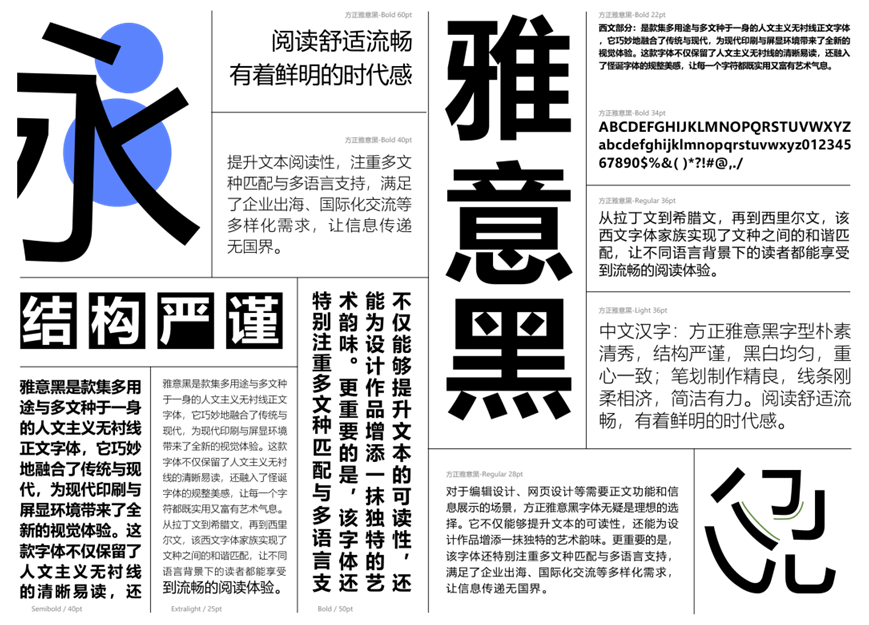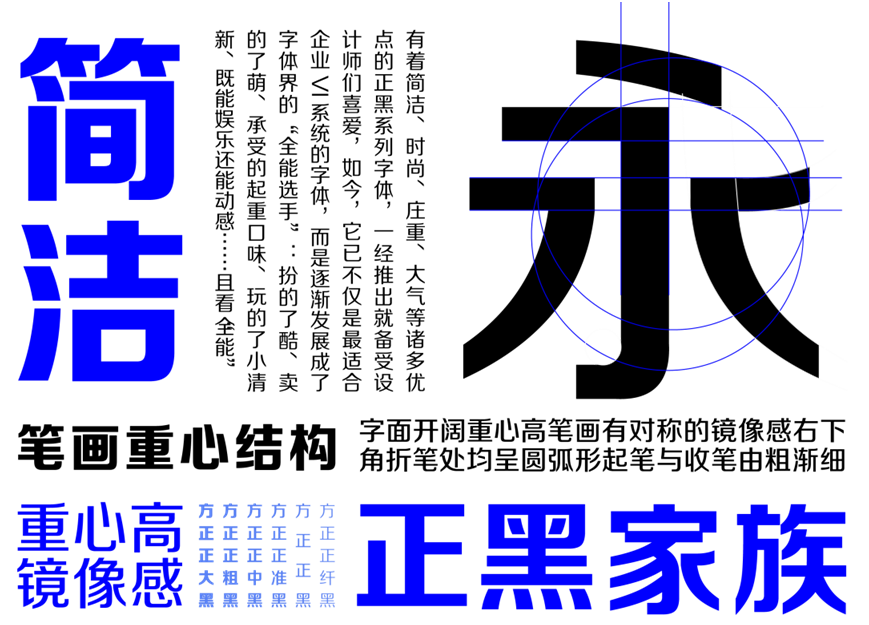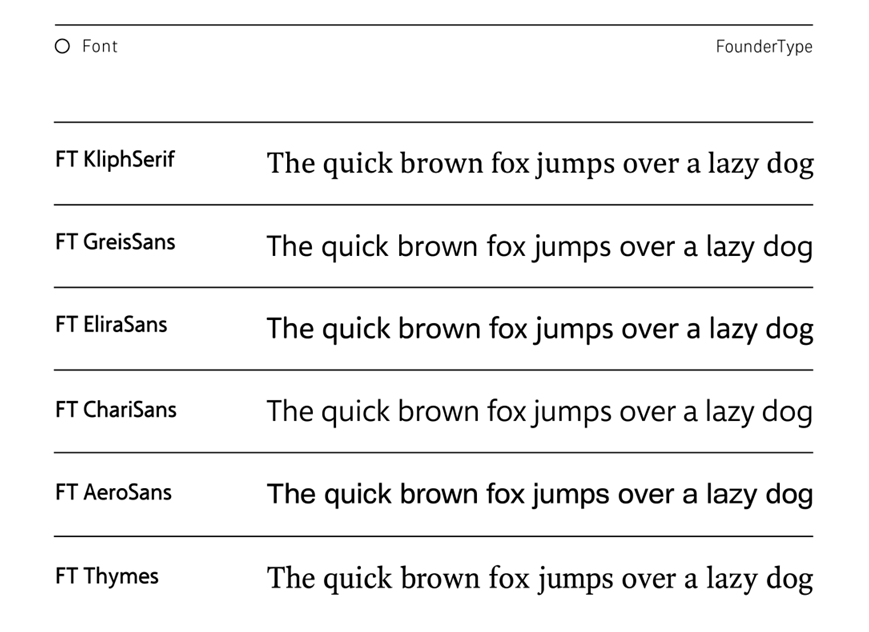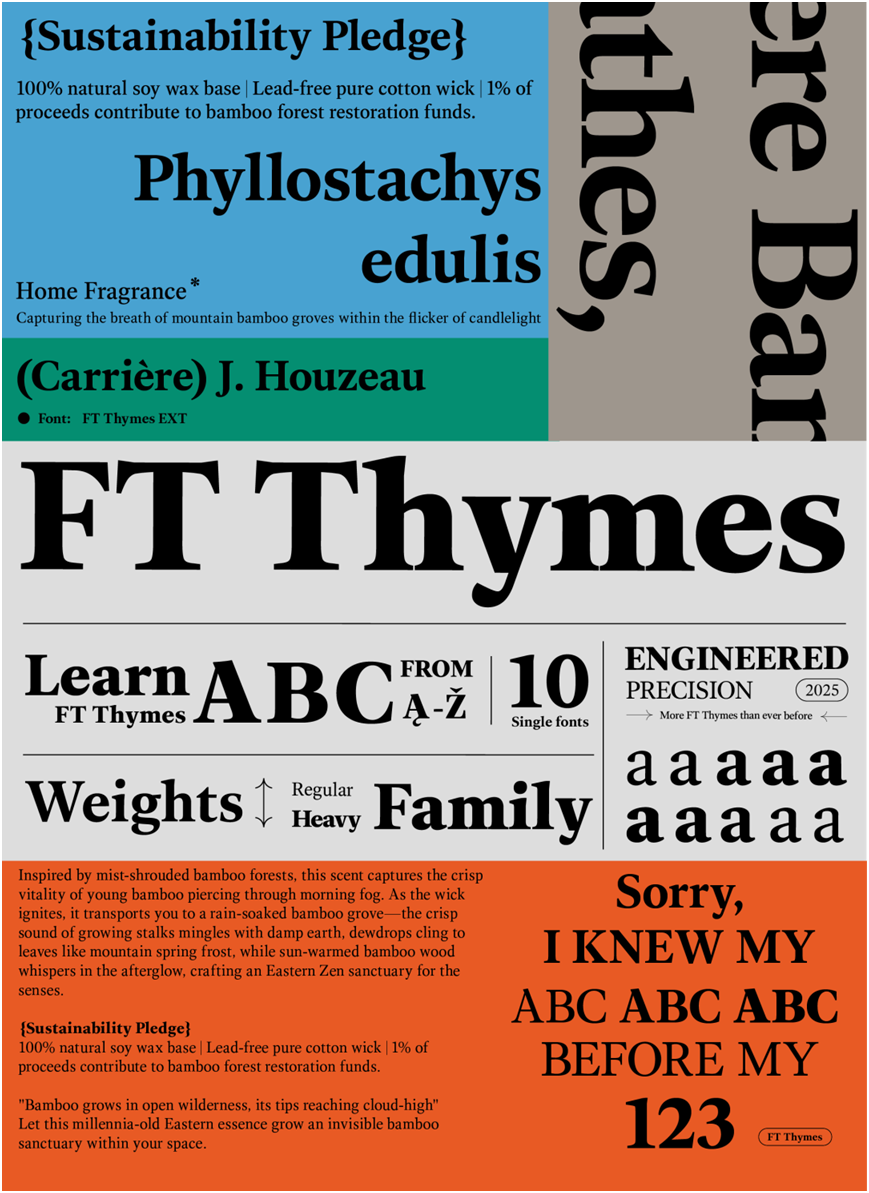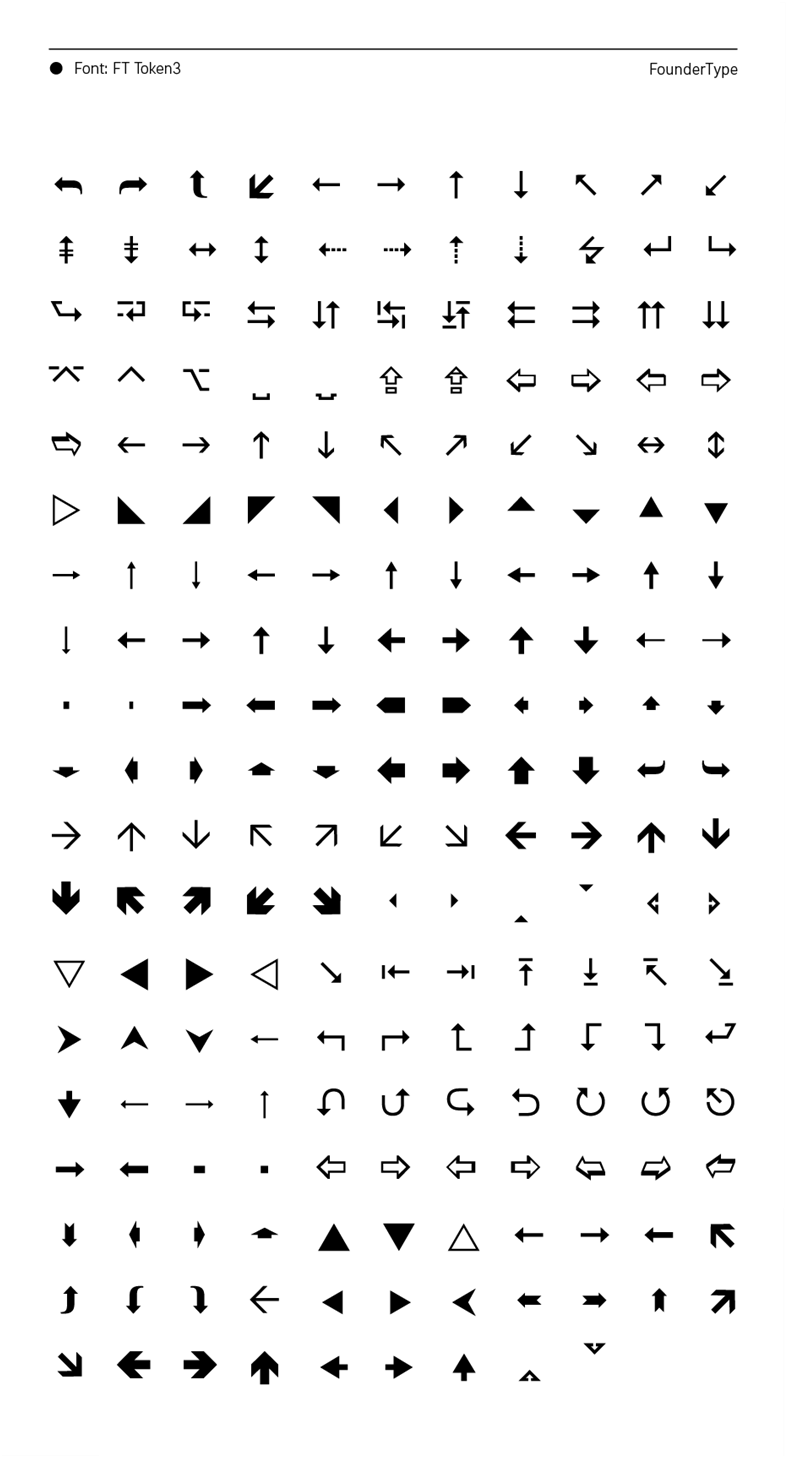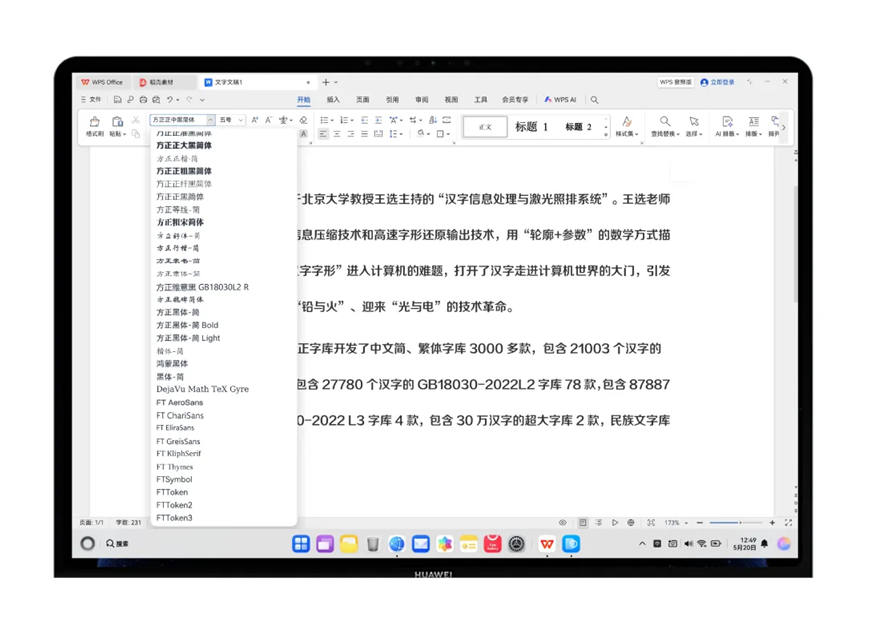
2025年5月19日,搭载华为鸿蒙操作系统的鸿蒙电脑,面向用户推出集AI智能、互联流畅、安全保障和精致体验于一体的全新办公系统。作为鸿蒙生态核心字体服务商,方正字库为此次提供了全面的系统字体支持,涵盖中文、西文及符号三大类字库,共计60款字体,覆盖政务、商务、教育、设计等多元办公场景。
在中文字库方面,方正字库为鸿蒙电脑提供了49款风格多样的中文字体,包括方正黑体、方正书宋、方正仿宋、方正楷体、方正等线、方正行楷、方正魏碑、方正隶书等常规字体,同时也内置了方正小标宋、方正粗宋、方正正黑、方正喵呜、方正舒体、方正手书等在创意设计与专业领域中广泛应用的特色字体。这些字体均经过字符集适配与系统级调优,支持GB18030-2022 L2、GB2312-80、BIG5等主流编码标准,确保文字显示的准确性和一致性。
西文字库:跨语言排版一致性突破
此外,为提升跨语言排版的协调性,方正字库同步为系统提供了6款西文字体,优化在演示文稿、办公文档的可视体验。西文字体在视觉规范和字形设计上与中文系统字体保持一致性,增强整体排版统一性。
符号字库:上千款符号优化办公可视化标准
在符号字体方面,方正字库提供了FT Symbol、FT Tokens等5款内嵌字库,包含1075个功能性符号和图标,覆盖办公常用图形、箭头与功能标识,进一步丰富办公文档中的视觉元素与信息传达效率。
文字排版:打造更规范的排版体验
针对文档、表格及演示材料等办公软件的实际应用需求,方正字库对系统字体进行了排版优化处理,提升整体版式适应性。字体间的风格、间距及字符规范实现协调统一,有效支持高标准的办公文件排版要求。
此次合作标志着方正字库与华为在国产操作系统生态建设中的进一步深化。通过提供多场景、全编码覆盖的系统字体解决方案,方正字库助力华为鸿蒙在提升用户办公体验方面迈出关键一步。
未来,双方将继续努力,面向智能办公时代的发展趋势,不断优化系统字体服务,拓展字体应用的场景广度与专业深度,为国产操作系统提供坚实的字体支持,推动自主软件生态高质量发展。